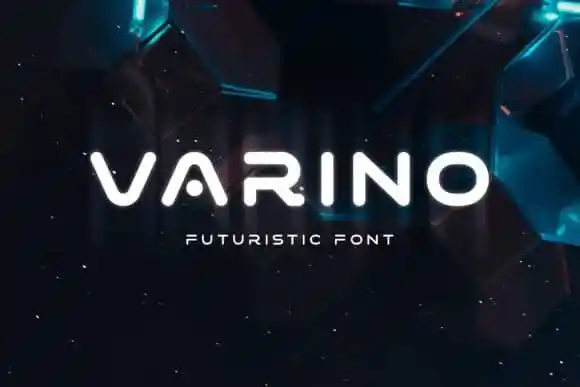
Varino Display Font – Download Grátis
Varino Display Font é uma família de tipo sans-serif futurista que inclui variâncias customizadas de sombra para um efeito 3D adicional. Criado pelo designer Arterfak, esta tipografia moderna e futurista se destaca por sua aparência limpa e arrumada. Com seus letras bem organizadas e elegantes, o Varino Display Font é perfeito tanto para projetos formais quanto não-formais. Este tipo de letra criará um impacto poderoso em qualquer design, destacando-se com sua simplicidade e modernidade. O Varino Display Font é uma opção ideal para quem busca uma fonte de display que transmite confiança e inovação na página ou no projeto, tanto em textos formais quanto informais.